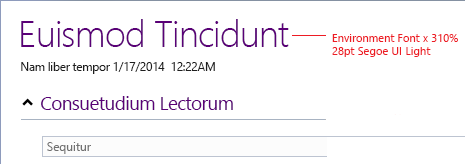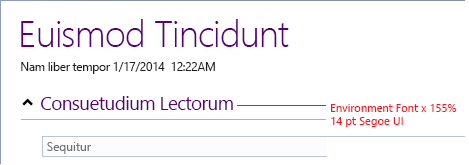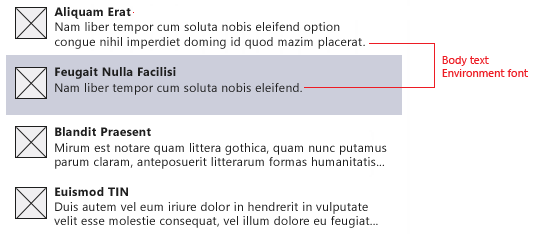
环境字体
Visual Studio 中的所有字体都必须向用户公开以供自定义。 这主要通过“工具选项”对话框中的“字体和颜色”页完成。 > 字体设置的三个主要类别包括:
环境字体 - IDE(集成开发环境)的主字体,用于所有界面元素,包括对话框、菜单、工具窗口和文档窗口。 默认情况下,环境字体绑定到当前版本的 Windows 中显示为 9 pt Segoe UI 的系统字体。 对所有界面元素使用一种字体有助于确保整个 IDE 中的字体外观一致。
文本编辑器 - 可以在“工具>选项”中的“文本编辑器”页中自定义代码和其他基于文本的编辑器中显示的元素。
特定集合 - 提供用户自定义界面元素的设计器窗口可能会在“工具>选项”的自己的设置页中公开特定于其设计图面的字体。
编辑器字体自定义和调整大小
用户通常会根据用户偏好(独立于常规用户界面)放大或缩放编辑器中文本的大小和/或颜色。 由于环境字体用于可能出现在编辑器/设计器中或作为编辑器/设计器的一部分的元素,因此当其中一种字体分类发生更改时,请务必注意预期行为。
创建显示在编辑器中但不属于 内容的 UI 元素时,必须使用环境字体,而不是文本字体,以便元素以可预测的方式调整大小。
对于编辑器中的代码文本,请使用代码文本字体设置调整大小,并响应编辑器文本的缩放级别。
接口的所有其他元素都应绑定到环境字体设置,并响应环境中的任何全局更改。 这包括但不限于:
上下文菜单中的文本
编辑器装饰中的文本,如灯泡菜单文本、快速查找编辑器窗格和导航到窗格
对话框中的标签文本,例如 “在文件中 查找”或 “重构”
访问环境字体
在 Native 或 WinForms 代码中,可以通过从SID_SUIHostLocale服务查询接口后调用方法IUIHostLocale::GetDialogFont来访问环境字体。
对于 Windows Presentation Foundation (WPF),请从 shell 的 DialogWindow 类而不是 WPF 类 Window 派生对话窗口类。
ShowModal 返回布尔值? (可为 null 的布尔值)与 DialogResult(如果需要)。 如果对话框已关闭且 正常,则返回值为 true。
如果需要显示一些不是对话框且托管在其自身HwndSource的 WPF UI,例如 Win32/WinForms 父窗口的弹出窗口或 WPF 子窗口,则需要设置 FontFamily WPF 元素的根元素。FontSize (shell 设置主窗口上的属性,但它们不会继承过 a HWND)。 shell 提供属性可绑定到的资源,如下所示:
格式设置(缩放/加粗)参考
某些对话框要求特定文本为粗体或环境字体以外的其他大小。 以前,大于环境字体的字体被编码为“”environment font +2或类似字体。 使用提供的代码片段将支持高 DPI 监视器,并确保显示文本始终以正确的大小和重量(如浅色或半光)显示。
注意
在应用格式设置之前,请确保遵循文本样式中的指南。**
若要缩放环境字体,请按指示设置 TextBlock 或 Label 的样式。 这些代码片段(正确使用)将生成正确的字体,包括适当的大小和粗细变化。
375% 环境字体 + 浅色
显示为: 34 pt Segoe UI 浅色
用于: (罕见)独特的品牌 UI
310% 环境字体 + 浅色
显示为: 28 pt Segoe UI 浅 色用途: 大型签名对话框标题,报表中的主标题
200% 环境字体 + 半灯
显示为:18 pt Segoe UI Semilight Use for: subheadings, titles in small and medium dialogs
155% 环境字体
显示为: 14 pt Segoe UI 用于: 文档井 UI 或报表中的节标题
| 用法: - 签名对话框中的标签和子标题 - 报表中的标签和子标题 - 文档井 UI 中的标签和子标题 应做事项: - 使用句子大小写 - 使用粗体粗细 禁止事项: - 斜体或粗斜体 - 用于正文文本 - 在标准 Visual Studio 控件中使用 - 在工具窗口中使用 |
显示为: 加粗 9 pt Segoe UI 可视化示例: ![]() |
环境字体
| 用法: 所有其他文本 Do: 使用句子大小写 不要: 斜体或粗斜体 |
显示为: 9 pt Segoe UI 可视化示例: ![]() |
填充和间距
标题需要它们周围的空间来给予他们适当的强调。 此空间因点大小和标题附近的内容而异,例如水平规则或环境字体中的文本行。
标题的理想填充应是大写字符高度空间的 90%。 例如,28 pt Segoe UI 浅色标题的上限高度为 26 pt,填充应约为 23 pt 或大约 31 像素。
标题周围的最小空间应为大写字符高度的 50%。 当标题附带规则或其他紧密拟合元素时,可以使用较少的空间。
粗体环境字体文本应遵循默认行高间距和填充。